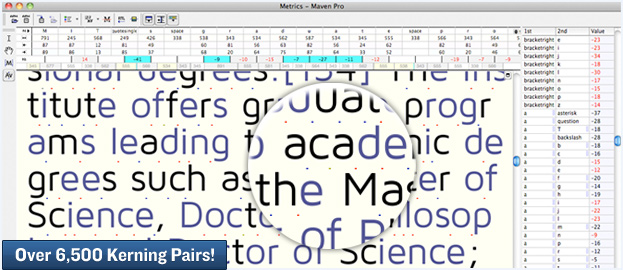
· Maven Pro (eine Grotesk von VISSOL)
Einem geschenkten Gaul ... und: ich kerne auch eher zu viel als zu wenig – aber so viele Kerningpaare sind entweder ein Zeichen für besonders tolle Qualität in einer Schrift mit großem Zeichenumfang, oder aber ein Zeichen für schlechte generelle Metrik oder Kerning-Klasseneinteilung ...
Der mexikanische Buchladen Ghandi verschenkt eine gleichnamige Schriftsippe: http://www.tipografiagandhi.com/
Free Harmonia Sans Sample Pack
Designed by Jim Wasco, the Harmonia Sans typeface family is a graceful blending of contemporary geometric sans serif lettershapes and classic calligraphic proportions. Consisting of 17 different stylings, Wasco undertook the design of the Harmonia Sans typeface with a single goal in mind. He recalls, “I wanted to create a simple and legible typeface that pulled from my favorite aspects of classic geometric sans designs, such as Futura and ITC Avant Garde Gothic.”
Diese -- für mich -- Display-Schrift soll auch in Textkörpern gut funktionieren, was ich noch nicht getestet habe. Aber in Displaygrößen gefällt sie mir doch:
Oranienburg
Eine Displayschrift
Der Autor, Joel Felix, schreibt zu seinem Werk:
Citizen Slab is a typeface that pays homage to a vintage aesthetic without losing its modern sensibility. Inspired by a recent trip to Boston, which stirred up a strong feeling of patriotism, I wanted to create a typeface that honored the days gone-by but was still relevant in todays design world.
Eine Brotschrift: http://fontfabric.com/sreda-free-font/
Von Elena Kowalski aus Ufa. Recht breit laufend und schön kräftig.
Noch eine Brotschrift: http://nymphont.deviantart.com/art/Aver-Font-302702408
Moin, anläßlich des letzten Adobe-Feigenblättchens fahndete ich nach einigen monospaced Freefonts (dicktengleiche Gratisschriftschnitte? Klingt irgendwie döofer) und fand diesen hier: http://www.fixedsysexcelsior.com/
Schöne Schrift ...
Aber die "iv"-Kombination im Schriftnamen ist ja doch kurz vor einer Kollision. Warum sowas nicht korrigiert wird – und sei es nur zum Schein und des schöneren ersten Eindrucks wegen – versteh ich nicht ganz ...